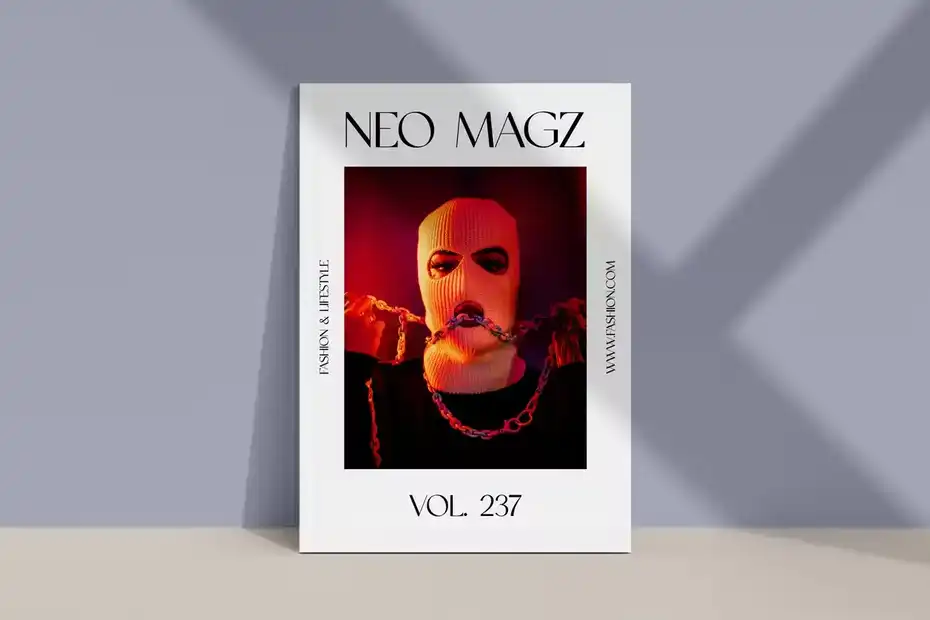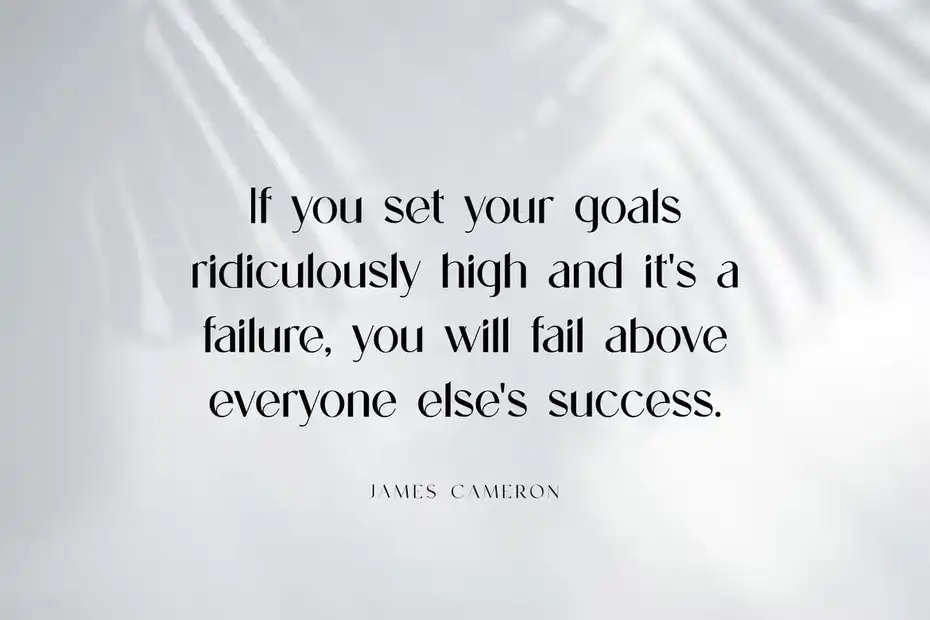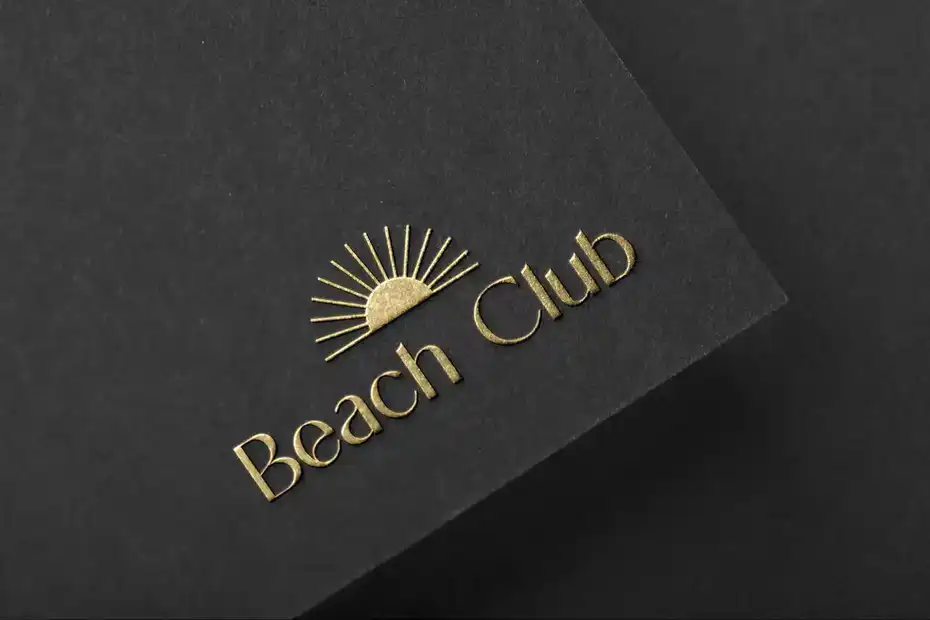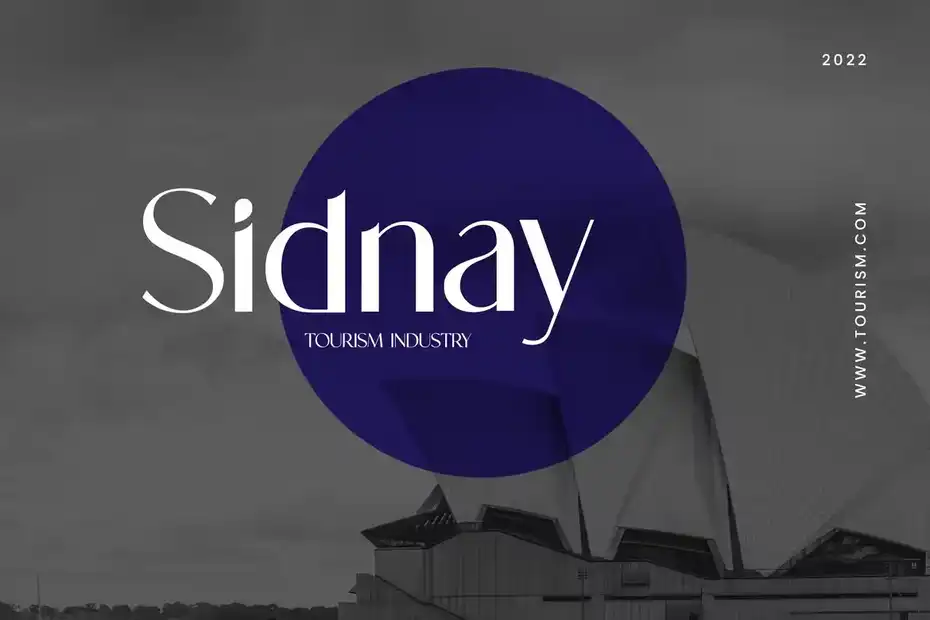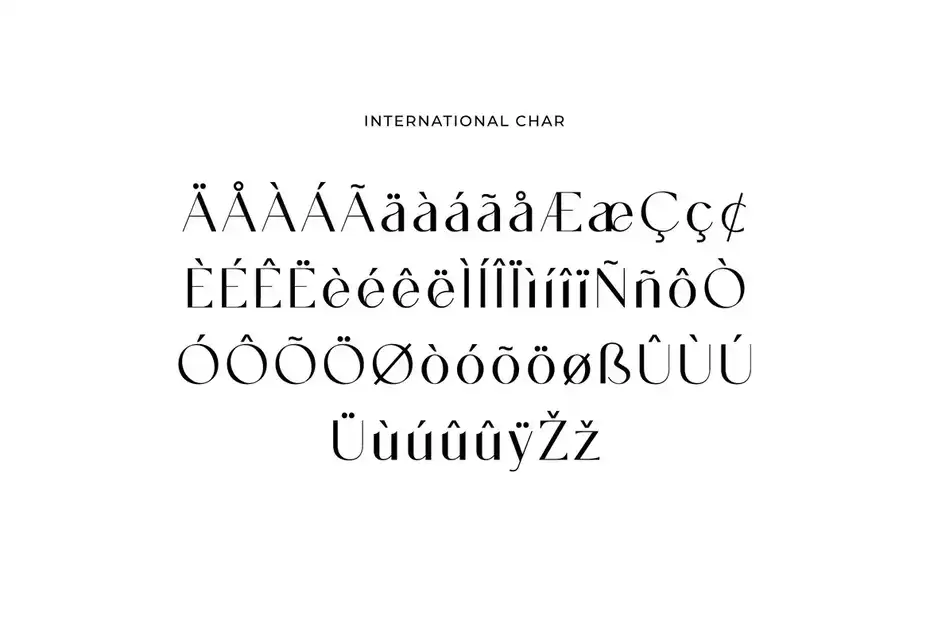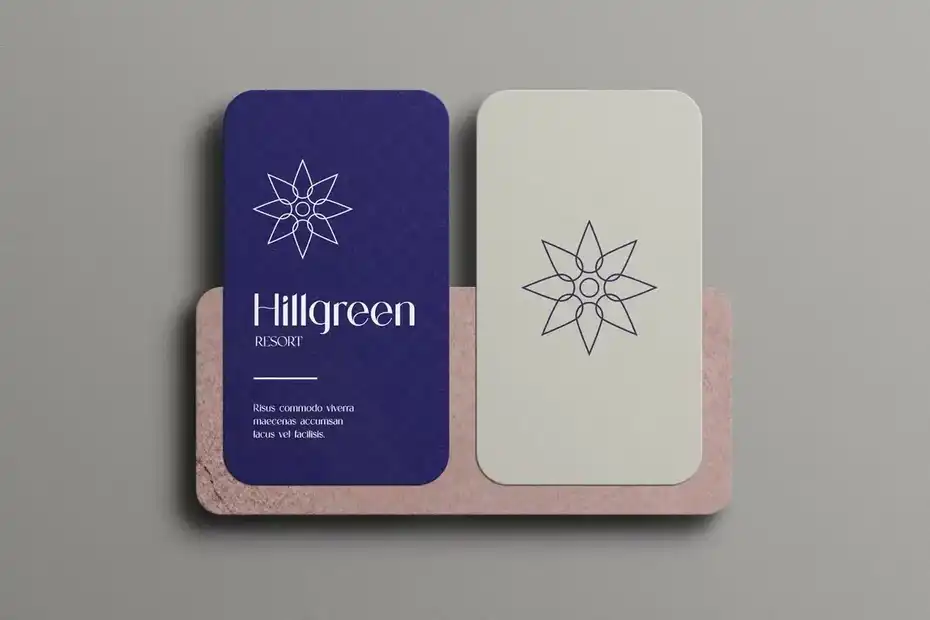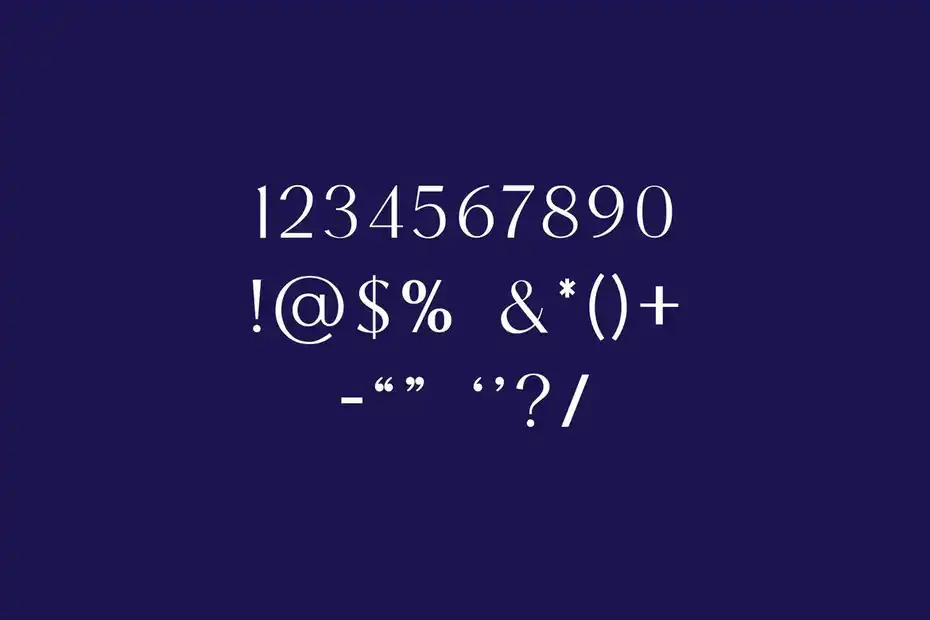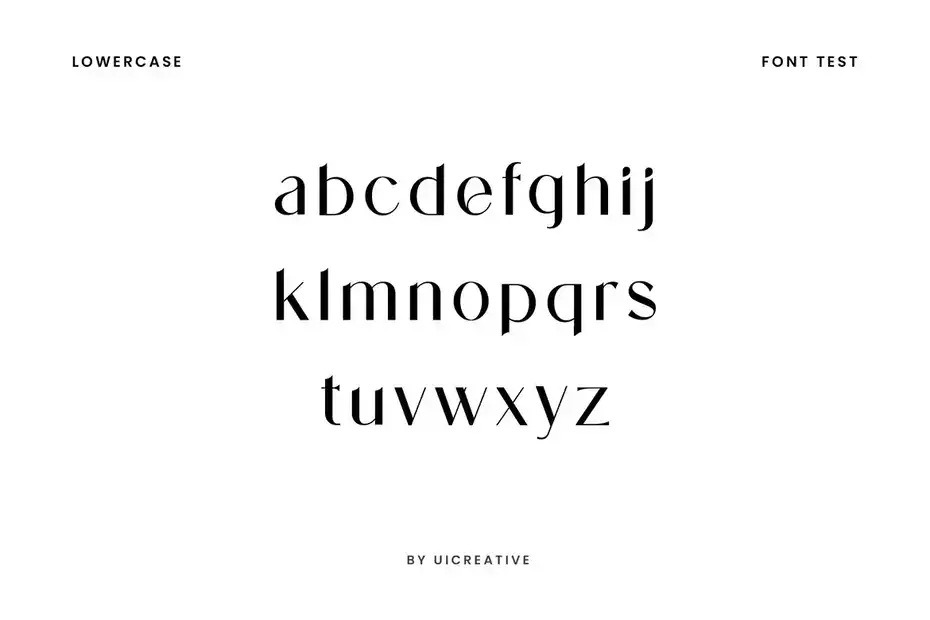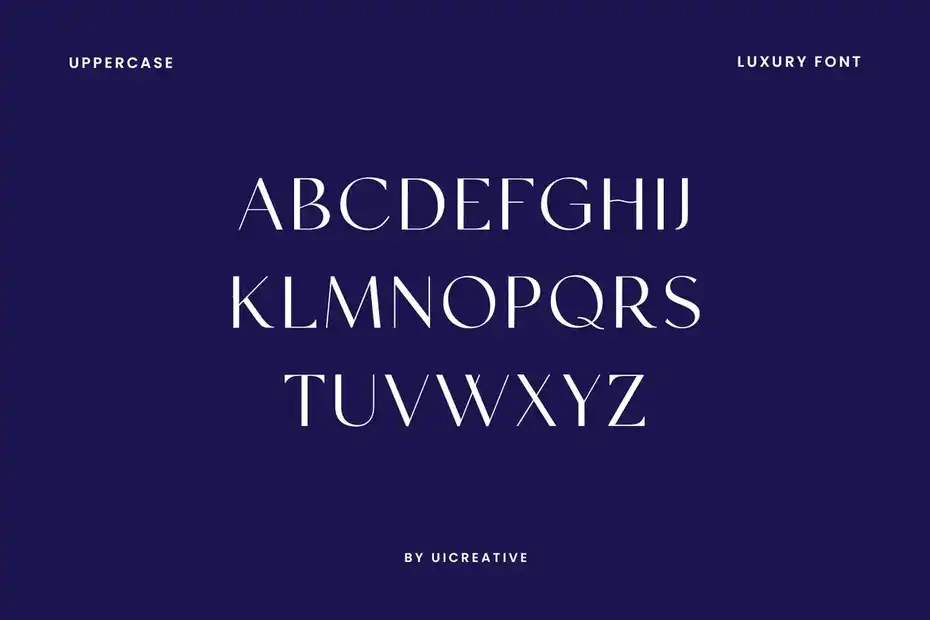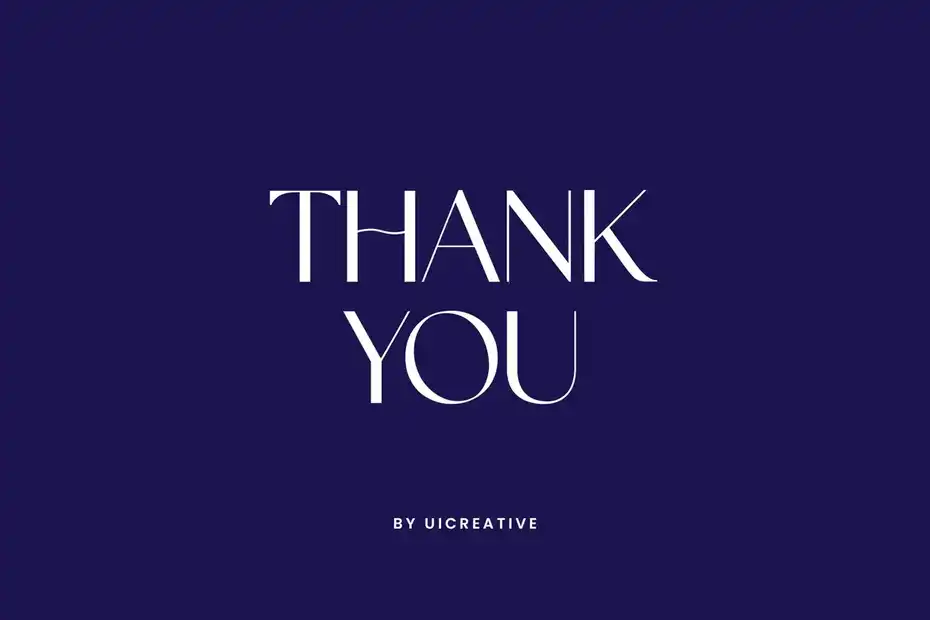
دانلود فونت انگلیسی Gilmoray Elegant Sans Serif Font
فونت انگلیسی Gilmoray Elegant Sans Serif Font : این فونت یک فونت مدرن Sans Serif است که برای پروژه های مختلف مانند: امضا، برندینگ، لوگو، عروسی، نقل قول تایپوگرافی، جلد مجلات یا کتاب، سربرگ وب سایت، لباس، طراحی بسته بندی و غیره مناسب میباشد.